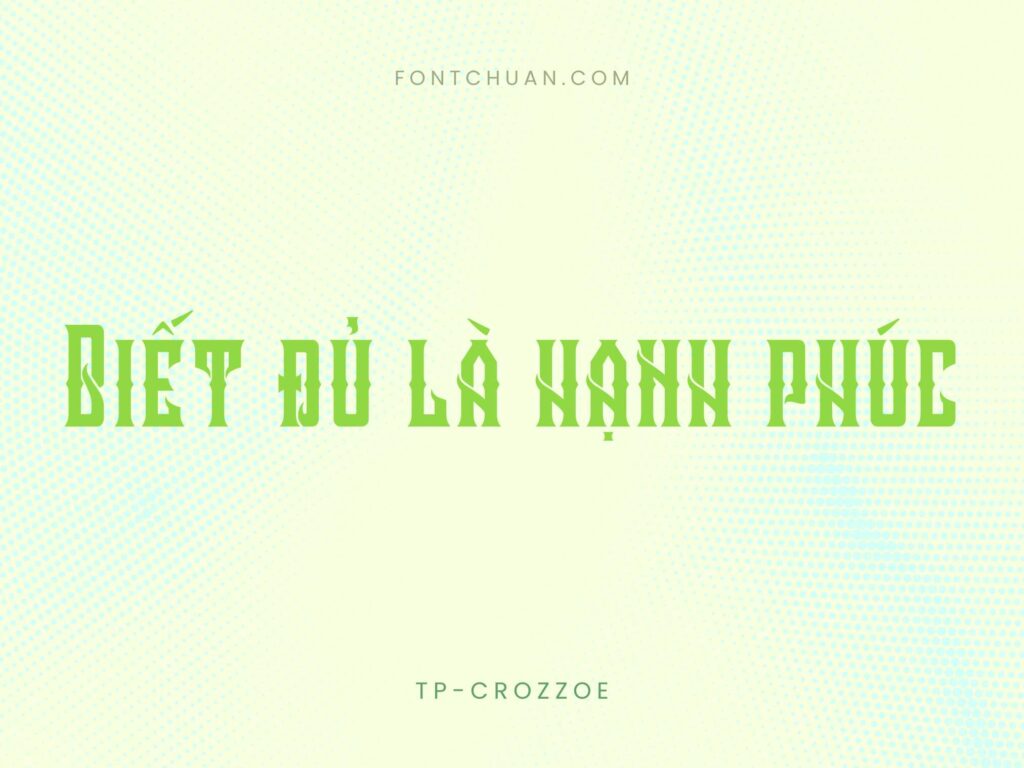
Font TP Crozzoe Việt Hóa
Crozzoe là một font chữ lấy cảm hứng từ phong cách Victoria, được thiết kế bởi Vacatype Co. Font này bao gồm đầy đủ các chữ cái viết hoa và viết thường, hỗ trợ đa ngôn ngữ và đi kèm với một số glyph bổ sung. Font đã được Việt hóa để hỗ trợ tiếng Việt bởi Tuỳn Pucca, giúp mở rộng phạm vi sử dụng trên toàn cầu. Font này được sưu tầm và chia sẻ bởi thành viên của Font Chuẩn, đáp ứng nhu cầu của người dùng và ứng dụng thực tế vào các dự án thiết kế.
Font này bao gồm đầy đủ các chữ cái viết hoa và viết thường, hỗ trợ đa ngôn ngữ và đi kèm với một số glyph bổ sung. Với vẻ ngoài cổ điển nhưng vẫn mang chút huyền bí, Crozzoe cũng có thể được xem là một Font chữ Halloween độc đáo, phù hợp cho các thiết kế mang không khí lễ hội hoặc chủ đề ma mị.
Đặc điểm thiết kế của Crozzoe bao gồm các nét chữ mang phong cách phương Tây, đậm chất cổ điển và tinh tế, rất thích hợp để sử dụng như một Font cổ trang trong các ấn phẩm lịch sử, thiệp mời, bìa sách hay poster mang phong cách hoài cổ. Đồng thời, với những đường nét góc cạnh và cấu trúc chữ mạnh mẽ, Crozzoe cũng có thể được biến tấu thành Font Gothic, mang lại vẻ huyền bí, ấn tượng và mạnh mẽ cho các tiêu đề, logo hoặc các dự án sáng tạo cần điểm nhấn đậm chất Gothic. Các ngành nghề phù hợp bao gồm quảng cáo, nghệ thuật, thiết kế đồ họa và xuất bản, giúp các sản phẩm trở nên độc đáo, thu hút và mang tính thẩm mỹ cao.